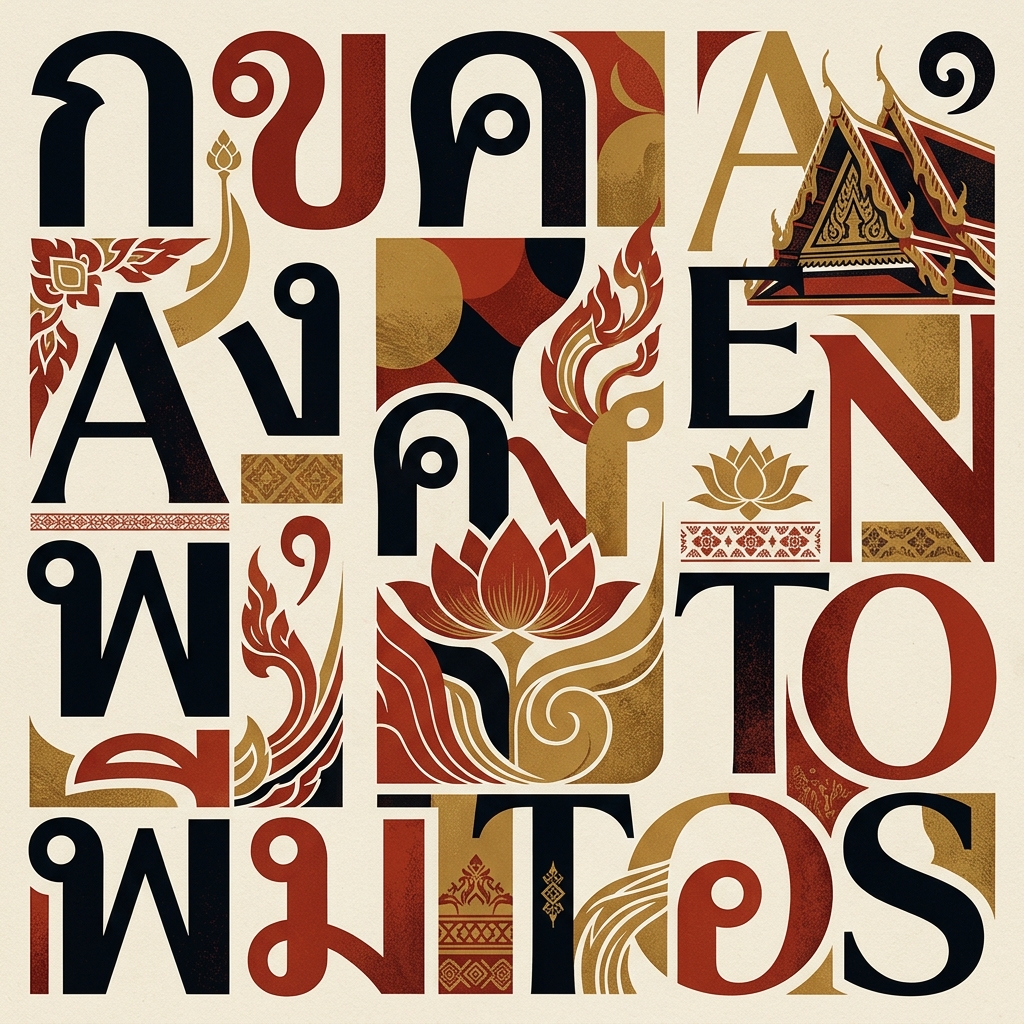
Browallia New
นักออกแบบ
Unity Progress
โรงหล่อตัวพิมพ์
Microsoft (bundled); Unity Progress (design)
น้ำหนัก
Regular, Bold
รองรับอักษรละติน
ใช่
Browallia New คืออะไร
Browallia New คือแซนส์ไทยแบบมีหัวที่ Unity Progress ออกแบบและติดมากับ Microsoft Windows มีสี่ไฟล์: Regular, Bold, Italic และ Bold Italic ประกาศลิขสิทธิ์ระบุปีออกแบบ 1992 (พ.ศ. 2535) พร้อมส่วนเพิ่มเติมโดย Monotype (2004) และ Microsoft (2015) เช่นเดียวกับ Angsana New และ Cordia New ฟอนต์นี้อยู่บนเครื่องหลายร้อยล้านเครื่องเพราะ Windows ใส่มาให้ ไม่ใช่เพราะมีใครเลือก
สามตระกูลนี้ครอบคลุมการจัดประเภทต่างกันในซีรีส์ UPC ของ Unity Progress: Angsana เป็นเซริฟ old-style, Cordia เป็นแซนส์เรขาคณิต ส่วน Browallia เป็นแซนส์ฮิวแมนนิสต์ — ได้อิทธิพลจากแซนส์เซริฟฮิวแมนนิสต์ตะวันตก เส้นสม่ำเสมอ บุคลิกคมสะอาด Browallia New คือรุ่นยุค Unicode ที่สืบทอดจาก BrowalliaUPC ต้นฉบับยุคโค้ดเพจทศวรรษ 1990
ใน typography สำนักงานไทย Browallia New เป็นตัวเลือกอันดับสามมาตลอด: ไม่ใช่ค่าเริ่มต้นของเอกสารเท่า Angsana New และไม่แพร่หลายในบทบาทแซนส์เท่า Cordia New มันโผล่ในสไลด์ สเปรดชีต และเทมเพลตของคนที่อยากได้แซนส์ไทยที่อุ่นกว่า Cordia เล็กน้อย
การออกแบบตัวอักษรและโทน
Browallia New เป็นแซนส์มีหัวสายฮิวแมนนิสต์: เส้นสม่ำเสมอ ช่องเปิดกว้าง และหัววงกลมเต็มบนพยัญชนะอย่าง ก ถ และ ภ โครงฮิวแมนนิสต์ให้ texture ที่นุ่มและเรียบกว่า Cordia New สายเรขาคณิตซึ่งเส้นโค้งเหมือนเขียนด้วยวงเวียนมากกว่า
ฟอนต์นี้จูนมาเพื่อการพิมพ์สำนักงานยุค 1990 และจอความละเอียดต่ำ และทุกวันนี้ก็ยังอ่านออกมาแบบนั้น ที่ 14–16pt ในเอกสาร Word มันทำหน้าที่ได้โดยไม่มีใครสังเกต ที่ขนาด display เส้นสม่ำเสมอจะดูบางและจืด และไม่มีน้ำหนักหนากว่า Bold มาช่วย วรรณยุกต์และสระวางตำแหน่งแบบระมัดระวัง ซึ่งช่วยให้เอกสารอ่านง่ายแต่ก็ทำให้บรรทัดหลวมตามแบบฉบับตระกูล UPC
ละตินที่แถมมาครอบคลุมโค้ดเพจ 1252 ปรับขนาดให้เข้าคู่กับตัวไทยสำหรับงานสำนักงานสองภาษา ใช้งานได้ แค่นั้น
น้ำหนักและการเผยแพร่
ที่มาของ Browallia New
การใช้งานที่เหมาะสม
Browallia New เหมาะกับเวิร์กโฟลว์ Microsoft Office บนเครื่อง Windows ภาษาไทย และแทบไม่เหมาะกับที่อื่นเลย โจทย์ที่พอรับได้:
ที่ไม่เหมาะ: การฝังบนเว็บ (ไลเซนส์ห้าม) งานแบรนด์และงานบรรณาธิการ (สองน้ำหนัก ลายเส้นตกยุค — งานแบบนั้นดู ฟอนต์ Kanit หรือ ฟอนต์ Prompt แทน) และโปรเจกต์ใหม่ทุกชนิดที่เริ่มจากศูนย์ เอกสารใหม่ในภาครัฐไทยควรใช้ TH Sarabun New ฟอนต์แห่งชาติที่เข้าแทนที่ตระกูล UPC ในงานราชการหลังปี 2553
การจับคู่
Browallia New เข้าคู่ภายในชุดฟอนต์ไทยของ Windows ที่มันติดมาด้วยกัน สามคู่: